싸인을 바꾸면 운이 바뀔 수 있을까요? 심리학적으로 보면 자신감 있는 싸인은 긍정적인 영향을 미칠 수 있어요. 성공한 사람들의 싸인을 살펴보면 공통적으로 강한 에너지가 담겨 있다는 점이 흥미롭죠! 🎯
내가 생각했을 때, 싸인은 단순한 서명이 아니라 자신의 정체성과 에너지를 담는 중요한 요소예요. 이제 성공한 사람들의 싸인을 살펴보고, 운을 부르는 싸인을 만드는 법을 알아볼까요? 🚀
싸인이 운과 성공에 영향을 줄까? 🍀
싸인을 바꾸면 운이 바뀔 수 있을까요? 사실 과학적으로 명확한 증거는 없지만, 자신감 있는 싸인은 긍정적인 영향을 줄 가능성이 높아요. ✅
🔹 싸인이 미치는 심리적 효과
✔ 자신감 상승 – 멋진 싸인을 갖고 있으면 서명할 때 당당해짐
✔ 브랜드 가치 상승 – 자신만의 스타일이 강하면 인지도 증가
✔ 일관성 유지 – 같은 싸인을 반복하면 신뢰도가 올라감
📌 싸인이 성공에 미치는 요소 ✨
요소 설명 자신감 당당하고 명확한 싸인은 긍정적인 인상을 줌 브랜드 아이덴티티 자신만의 개성을 담으면 브랜드 가치 상승 일관성 같은 싸인을 반복하면 신뢰도 상승 운과 상징성 운을 불러오는 기호(⭐, 🍀, 🔥)를 포함 가능 이제 성공한 사람들의 싸인 공통점을 살펴볼까요? 🔎
성공한 사람들의 싸인 공통점 🔎
성공한 사람들의 싸인을 살펴보면 몇 가지 공통된 특징이 있어요. 이들은 싸인을 단순한 서명이 아니라, 자신의 브랜드와 에너지를 담은 상징으로 활용해요. ✨
🔹 성공한 사람들의 싸인 특징
✔ 자신감 있는 크고 명확한 글씨
✔ 필기체처럼 부드럽고 자연스러운 흐름
✔ 한눈에 알아볼 수 있도록 독창적인 디자인
✔ 싸인의 끝이 위를 향하는 상승 곡선 (긍정적 기운)
📌 성공한 사람들의 싸인 스타일 분석 💡
공통점 설명 대표적인 예 크고 명확한 글씨 자신감과 당당함을 표현 도널드 트럼프, 일론 머스크 필기체 스타일 흐름이 자연스러워 보임 빌 게이츠, 오프라 윈프리 독창적인 디자인 브랜드화된 스타일 스티브 잡스, 리처드 브랜슨 상승 곡선 긍정적인 에너지를 담음 워런 버핏, 제프 베이조스 이제 운을 부르는 싸인의 특징을 알아볼까요? 🌟
운을 부르는 싸인의 특징 🌟
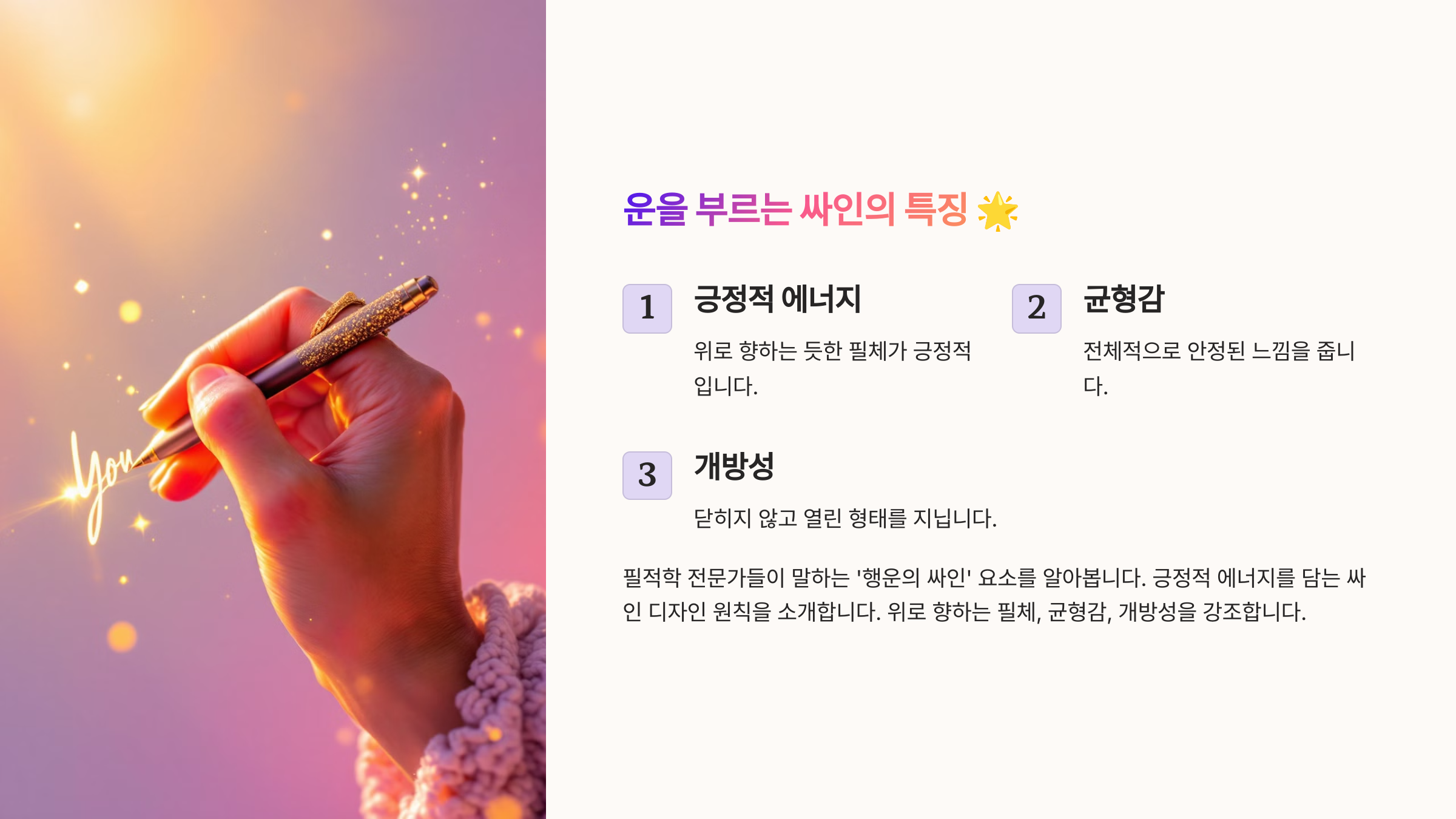
싸인에 따라 긍정적인 에너지를 담을 수도 있어요. 특히, 운이 좋다고 알려진 사람들의 싸인을 보면 공통적인 특징이 있답니다! 🍀
🔹 운이 좋아 보이는 싸인의 특징
✔ 오른쪽 위로 올라가는 싸인 (성장과 번영의 의미)
✔ 부드럽고 자연스러운 흐름 (긍정적인 에너지 전달)
✔ 기호(⭐, 🍀, 🔥)를 포함하여 행운 상징
✔ 첫 글자 강조하여 강한 인상 남기기
📌 운 좋은 싸인의 핵심 요소 ✍
특징 설명 오른쪽 상승형 싸인의 끝이 위로 올라가면 긍정적인 느낌 부드러운 곡선 자연스러운 흐름이 안정감을 줌 행운의 기호 포함 ⭐, 🍀, 🔥 같은 심볼을 활용해 운을 끌어옴 첫 글자 강조 이니셜이나 첫 글자를 강하게 표현 이제 성공한 기업인의 싸인 스타일을 살펴볼까요? 💼
성공한 기업인의 싸인 스타일 💼
기업인들의 싸인은 신뢰감과 권위를 나타내는 요소가 많아요. 특히, 글로벌 CEO들의 싸인을 보면 깔끔하면서도 강렬한 인상을 주는 디자인이 많답니다. 💼
🔹 성공한 기업인의 싸인 특징
✔ 깔끔하고 직선적인 디자인 (비즈니스에서 신뢰감 상승)
✔ 이니셜을 활용한 간결한 서명
✔ 싸인의 끝을 길게 마무리해 안정감 제공
✔ 필기체 느낌으로 자연스러운 흐름 유지
📌 유명 기업인의 싸인 분석 ✍
기업인 싸인 특징 대표적인 요소 일론 머스크 간결하면서도 힘 있는 필기체 이니셜 "E.M" 강조 빌 게이츠 깔끔하고 명확한 필기체 일관된 흐름 유지 워런 버핏 싸인의 끝을 길게 마무리 안정감 있는 디자인 제프 베이조스 곡선이 부드러운 서명 필기체 스타일 이제 운이 좋아 보이는 싸인 만들기 방법을 알아볼까요? ✍
운이 좋아 보이는 싸인 만들기 ✍
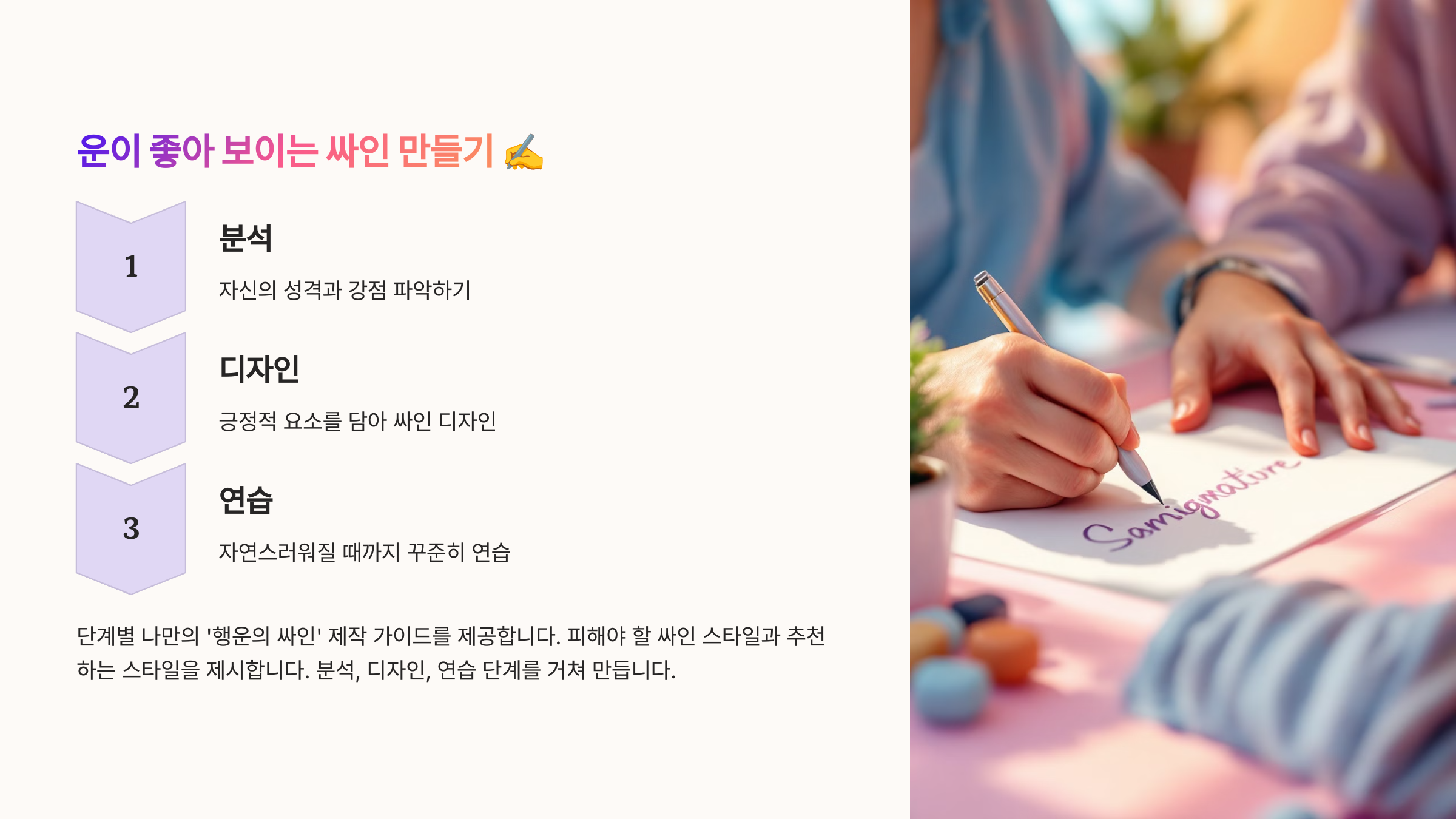
운이 좋아 보이는 싸인은 단순한 글씨가 아니라 긍정적인 에너지를 담은 디자인이에요. 싸인을 조금만 수정해도 성공적인 이미지와 강한 인상을 줄 수 있어요! 🚀
🔹 운 좋은 싸인을 만드는 방법
✔ 싸인의 끝을 위로 향하게 디자인 (성장과 발전의 의미)
✔ 부드럽고 자연스러운 흐름 유지 (긴장감 없는 스타일)
✔ 첫 글자를 강조하여 강한 인상 남기기
✔ 행운의 기호(⭐, 🍀, 🔥)를 추가하여 긍정적인 기운 담기
📌 운을 부르는 싸인의 핵심 요소 ✨
요소 설명 오른쪽 상승형 싸인의 끝이 위로 향하면 긍정적인 느낌 자연스러운 흐름 끊기지 않고 부드러운 필기체가 좋음 첫 글자 강조 이니셜을 크게 작성하여 강한 인상 남기기 행운의 기호 포함 ⭐, 🍀, 🔥 같은 심볼 추가 이제 운 좋은 싸인을 유지하는 방법을 알아볼까요? 🔮
운 좋은 싸인을 유지하는 방법 🔮
운이 좋아 보이는 싸인을 만들었다면, 일관성 있게 유지하는 것이 중요해요. 싸인이 자주 바뀌면 신뢰도가 떨어질 수 있기 때문에, 꾸준한 연습과 관리가 필요해요. ✨
🔹 운 좋은 싸인을 유지하는 4가지 방법
✔ 매일 일정한 스타일로 싸인 연습하기 (손이 기억하도록)
✔ 중요한 문서에는 같은 싸인을 사용하여 신뢰도 유지
✔ 디지털 싸인도 동일한 스타일로 만들기
✔ 필요하면 기호(⭐, 🍀)를 추가하여 상징성 부여
📌 운 좋은 싸인을 유지하는 습관 ✍
방법 설명 일관된 연습 매일 같은 스타일로 연습하여 습관화 공식 문서에 동일한 싸인 계약서, 금융 서류 등에서 신뢰감 유지 디지털 싸인 활용 전자 서명도 동일한 스타일로 만들기 운 좋은 요소 추가 행운을 상징하는 기호를 포함 이제 싸인에 대한 궁금증을 해결할 시간! FAQ에서 자주 묻는 질문을 정리해볼까요? ❓
FAQ ❓
Q1. 싸인을 바꾸면 정말 운이 바뀔까요?
A1. 과학적으로 입증된 것은 아니지만, 싸인을 바꾸면서 자신감과 긍정적인 마음가짐을 갖는다면 좋은 영향을 줄 수 있어요. 특히, 오른쪽 위로 올라가는 싸인은 성장과 성공을 의미하는 상징적인 요소로 여겨져요. ✨
Q2. 성공한 사람들의 싸인에서 배울 점이 있나요?
A2. 네! 성공한 사람들의 싸인은 크고 명확하며, 자연스러운 흐름을 가지고 있어요. 싸인의 끝을 길게 마무리하거나, 필기체 스타일을 적용하면 신뢰감을 줄 수 있어요. 💼
Q3. 싸인을 더 멋지게 만들려면 어떻게 해야 하나요?
A3. 싸인을 멋지게 만들려면 ✅ 첫 글자를 강조하고 크기를 조절하기 ✅ 부드럽고 자연스러운 필기체로 연결하기 ✅ 기호(⭐, 🍀, 🔥)를 추가하여 개성을 살리기 ✅ 빠르고 일관되게 싸인 연습하기 이런 요소를 추가하면 더욱 세련된 싸인을 만들 수 있어요! ✍
Q4. 싸인을 바꾸면 법적으로 문제될까요?
A4. 공식 문서나 금융 서류에서는 등록된 싸인을 유지하는 것이 중요해요. 새로운 싸인으로 변경하려면 은행이나 공공기관에 미리 업데이트하는 것이 좋아요. ✅
Q5. 디지털 싸인은 어떻게 만들 수 있나요?
A5. 태블릿이나 스마트폰에서 스타일러스 펜을 이용해 싸인을 작성한 후 PNG 파일로 저장하면 활용할 수 있어요. 또한, Adobe Sign, DocuSign 같은 전자 서명 도구를 사용하면 더욱 편리해요. 💻
Q6. 싸인의 크기는 어느 정도가 적당할까요?
A6. 싸인은 너무 크면 문서에서 공간을 많이 차지하고, 너무 작으면 가독성이 떨어질 수 있어요. A4 용지, 명함, 포스트잇 등 다양한 크기로 테스트하면서 적절한 크기를 찾는 것이 좋아요. 📏
Q7. 싸인에 기호를 넣으면 더 운이 좋아질까요?
A7. 심리적으로는 긍정적인 영향을 줄 수 있어요! ⭐, 🍀, 🔥 같은 행운의 기호를 싸인에 포함하면 자신감이 올라가고 긍정적인 인상을 줄 수 있어요.
Q8. 싸인을 빠르게 연습하는 방법이 있나요?
A8. 싸인을 빠르게 익히려면 1⃣ 눈 감고 싸인 연습 (손의 감각 익히기) 2⃣ 다양한 크기로 싸인 연습 (A4, 명함, 포스트잇) 3⃣ 빠른 속도로 싸인 연습 (5초 이내에 완성 목표) 4⃣ 거울을 보며 싸인 확인 (다른 사람이 볼 때 느낌 체크) 이 방법을 활용하면 더욱 멋진 싸인을 완성할 수 있어요! 🚀
이제 싸인 만들 때 실수하지 않고, 완벽한 나만의 싸인을 완성할 수 있겠죠? 🎯 꾸준히 연습해서 멋진 싸인을 만들어보세요! ✨